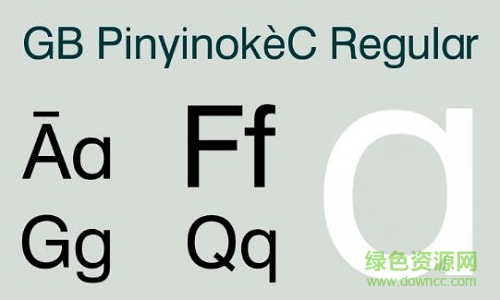
软件介绍 软件标签: pinyinok字体 英文字体 gb pinyinok-c字体是一款常出现在小学教学资料上的拼音字体,该字体简洁爽朗,可以用过键盘输入带音标的各种字母,操作非常简单,需要的朋友快来下载吧!字体特征【老式字体】老式字体往往有衬线,反映出传统字体设计的特征。老式字体字母往往会有倾斜的轴线,这是镌刻字体的凿子类工具所特有的痕迹。【过渡性字体】过渡性字体也有衬线,但字母中粗细线条的反差没有老式字体那么明显,而且其轴线也趋于垂直。字体本身看起来更清晰,具有手工绘制的特色gb pinyinok-c字体安装方法1、点击打开字体,直接选择安装即可。2、将字体复制到C:\Windows\Fonts文件夹即可完成安装。 软件截图 上一张下一张(1 / 1) 安装详细截图 其他版本下载 标题 大小 更新日期 下载 下载地址 电脑版 gb pinyinok c 点击报错 软件无法下载或下载后无法使用,请点击报错,谢谢! 关闭报错反馈 请描述您所遇到的错误,我们将尽快予以修正,谢谢! *必填项,请输入内容 本类最新 dreamweaver字体库 首尔南山体字体 v1.06 官方版 潮字社风云简ttf 潮字社凌渡鲲鹏简体字体 潮字社曾玉波手书简字体 微博慧心字体 相关文章 Linux 防火墙配置基础篇 教你在Red Hat Linux 9下架设FTP服务器 新手如何远程管理windows2003服务器 Linux下FTP的配置与应用 LINUX下MYSQL完全安装使用指南 linux网站建立步骤 用户评论 热门评论 最新评论 发表评论 查看所有评论(0) 昵称: 请不要评论无意义或脏话,我们所有评论会有人工审核. 字数: 0/500 (您的评论需要经过审核才能显示)